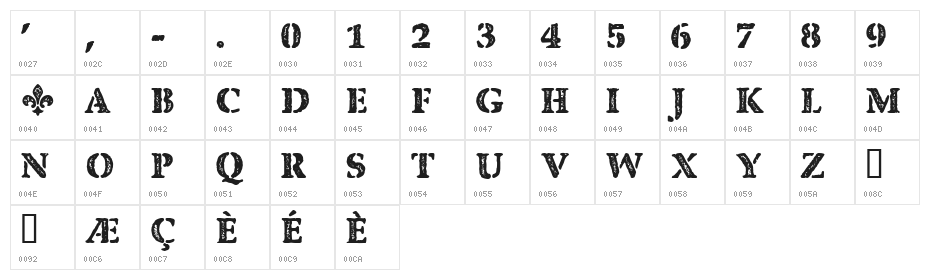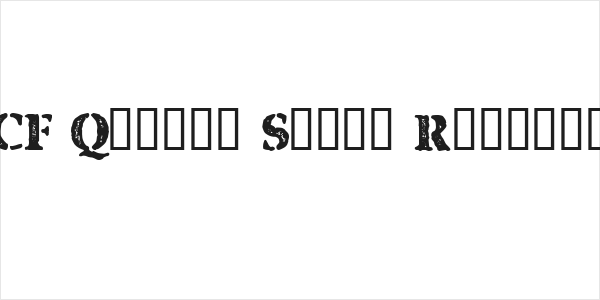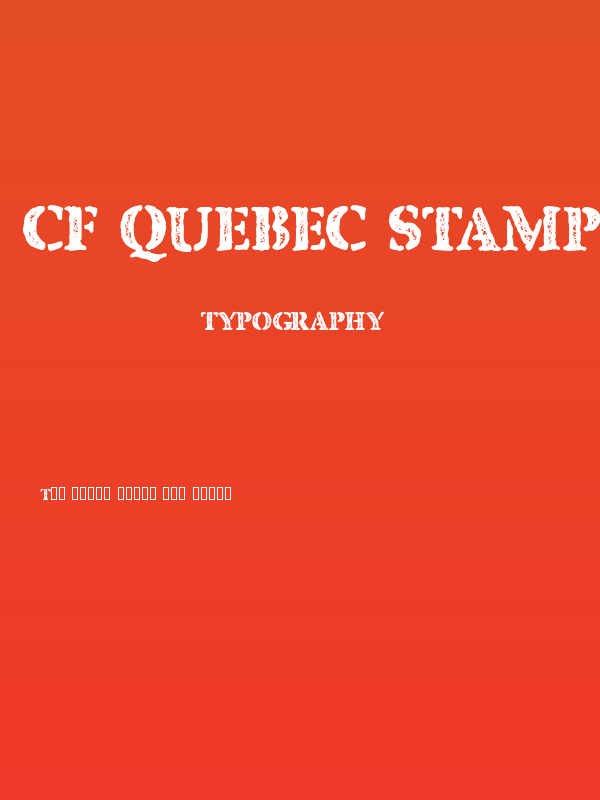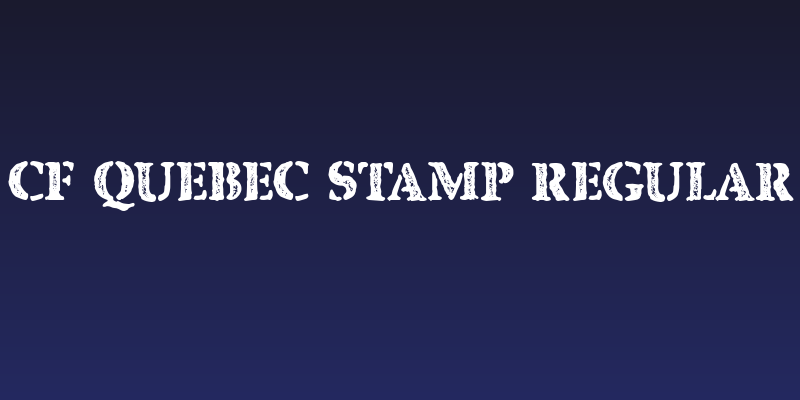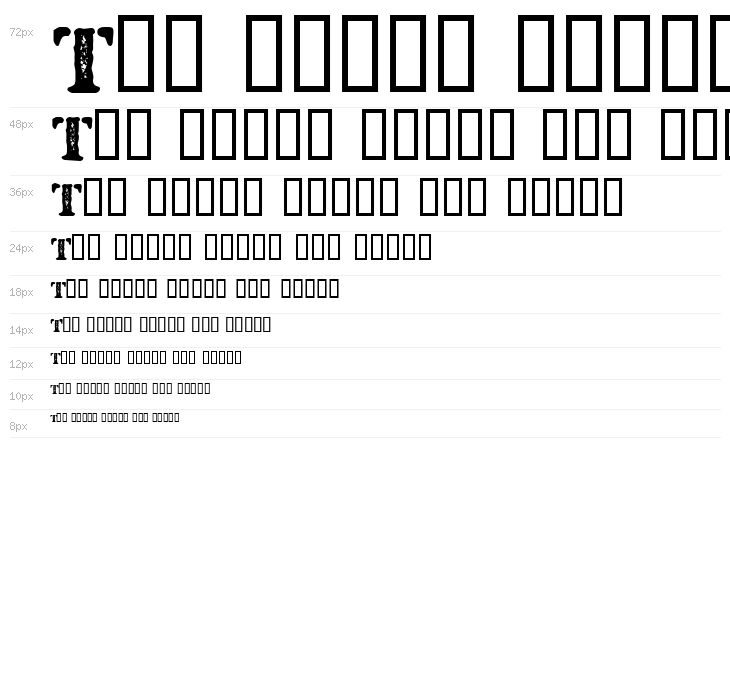
CF Quebec Stamp Regular Font
| Progetti proposti | Ideal for vintage-themed designs, posters, branding for artisanal products, and any project needing a rustic, authentic touch. |